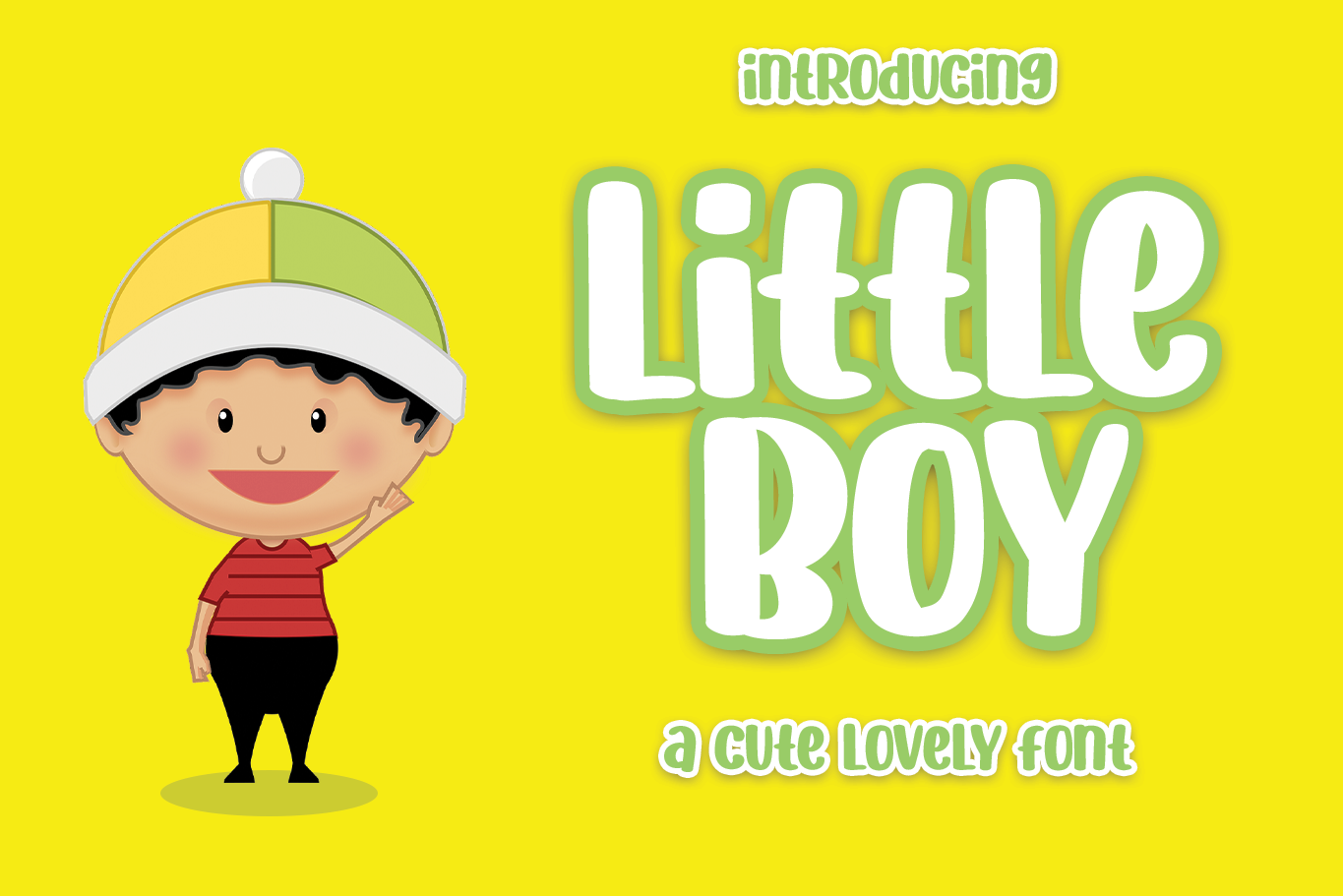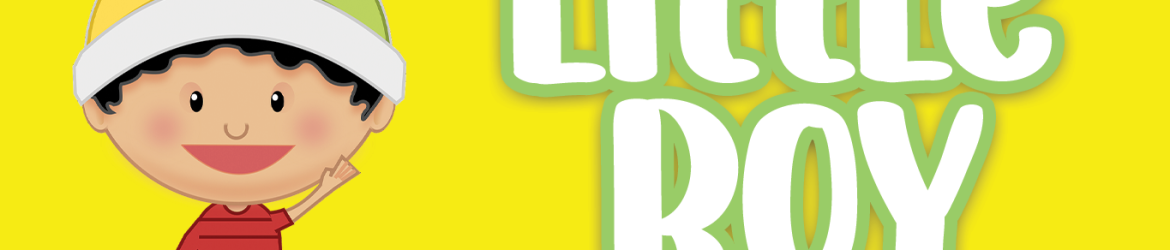
Little Boy Display Font – Download Grátis
Esta é uma fonte de display fofa e alegre, ideal para temas infantis. Ela se adequa perfeitamente para projetos visuais que trazem vida às letras, especialmente quando combinada com cores vibrantes. A Little Boy Display Font é certamente o tipo certo para criar um design animado e divertido, especialmente nos estilos de ilustração ou arte educacional focados em crianças. Seja ela uma parte essencial de sua próxima campanha publicitária infantil ou a cara ideal para adicionar ao seu portfolio de projetos digitais, essa fonte é certamente um recurso valioso no seu arsenal criativo. Não perca tempo — experimente Little Boy Display Font hoje mesmo!